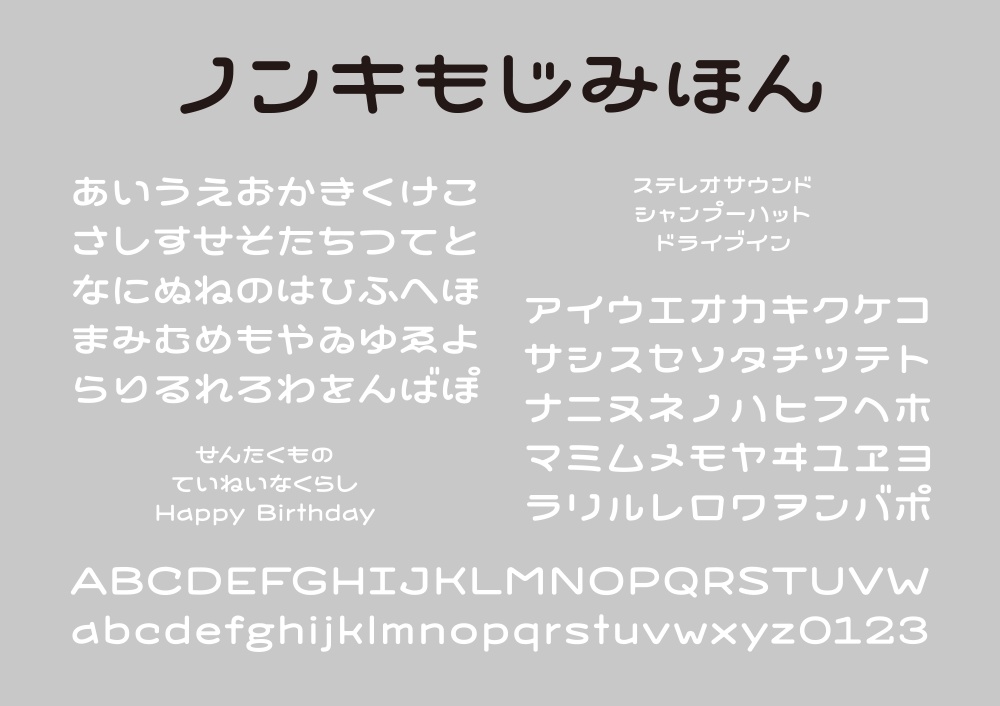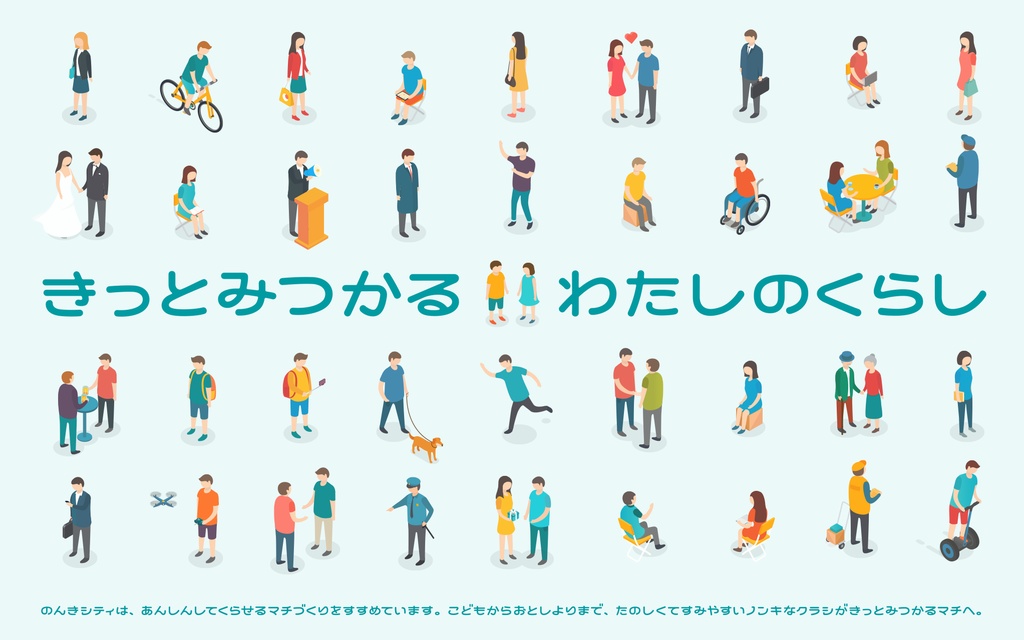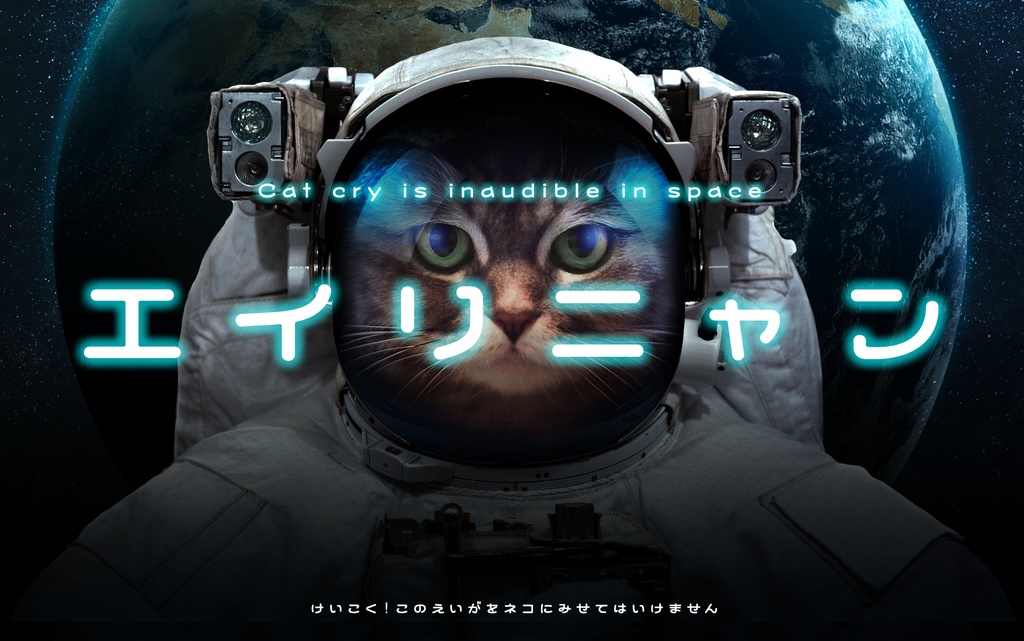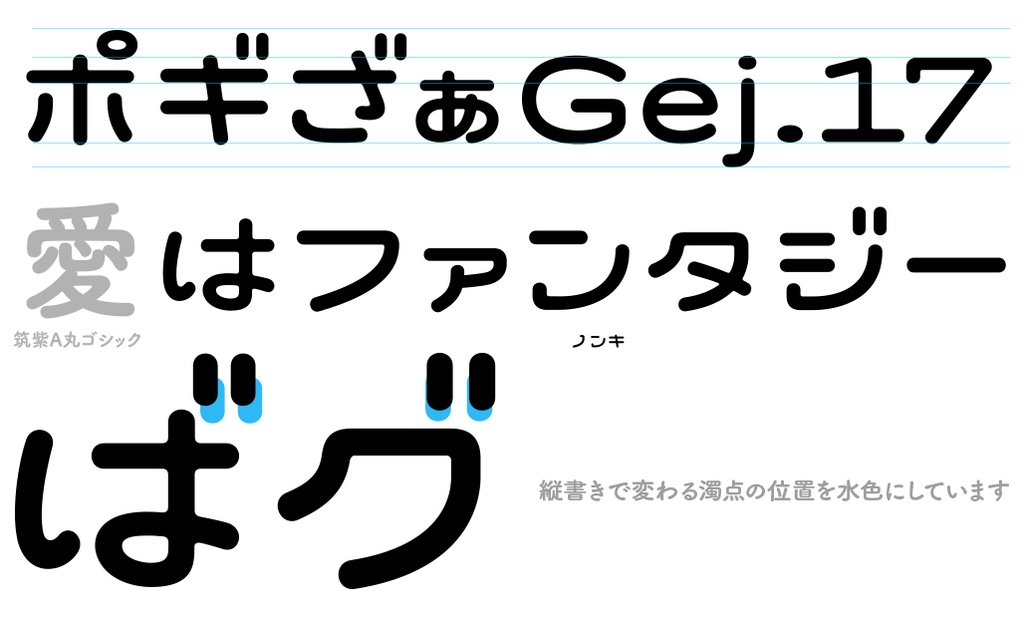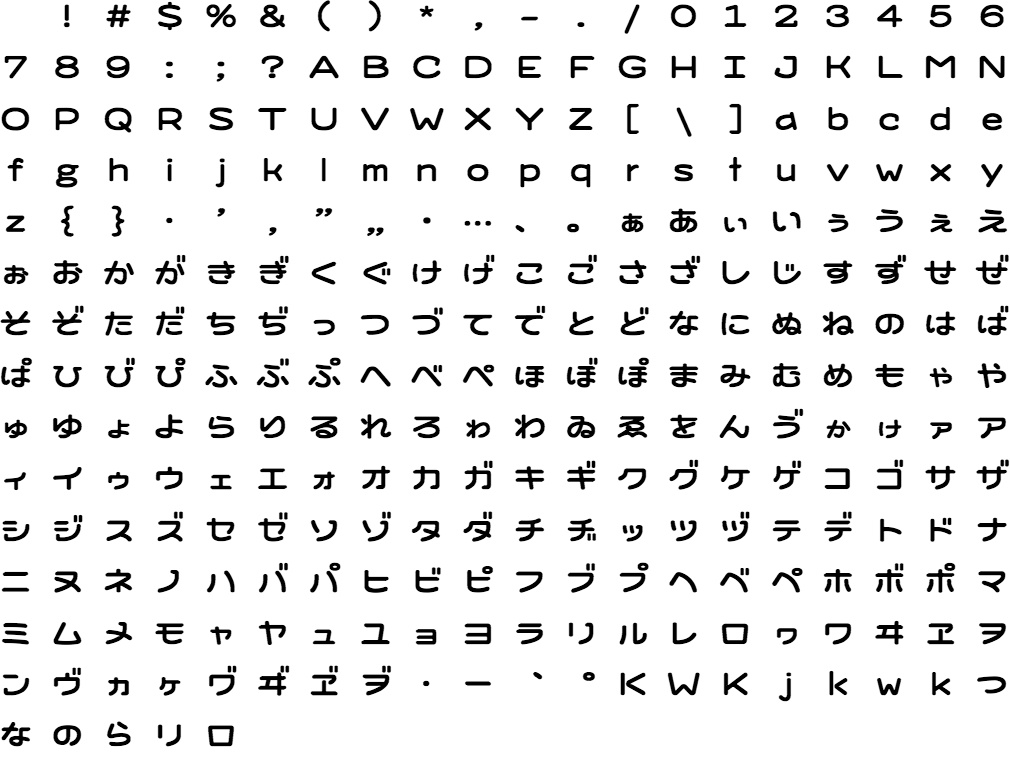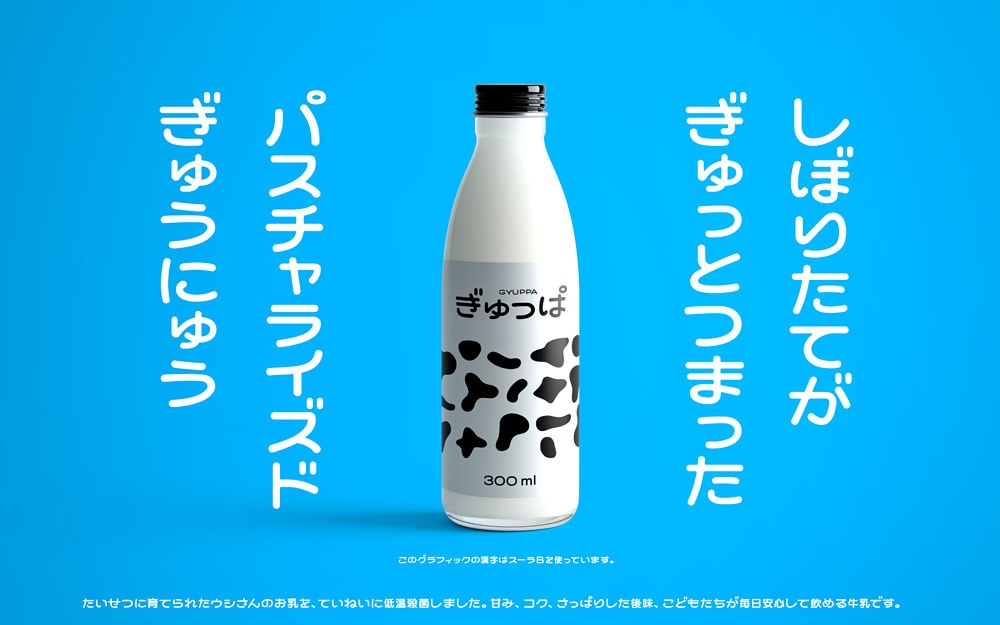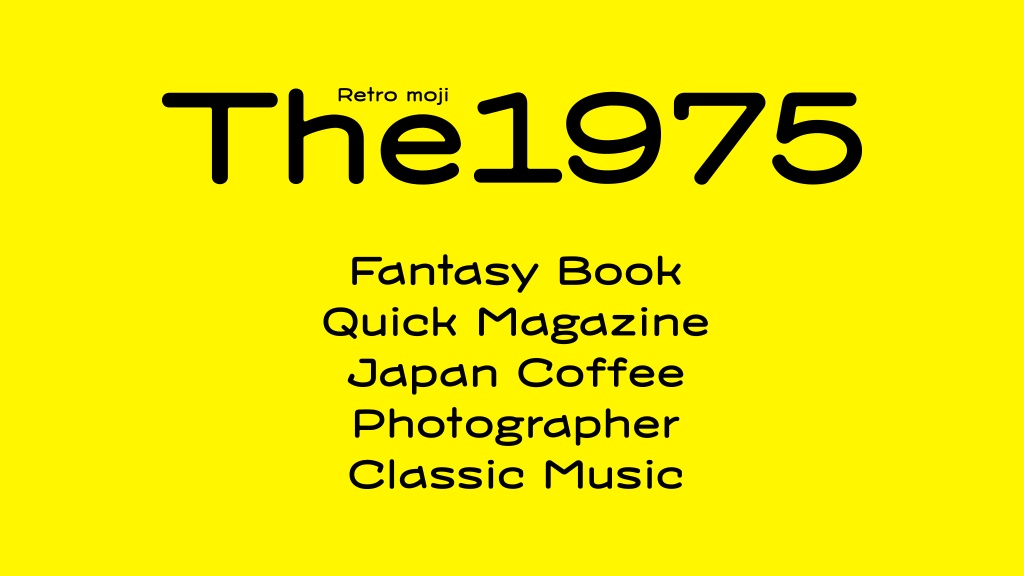
ノンキフォント
ノンキフォント のんきでかっこいい70年代風フォント 1970年代のテレビテロップ文字からインスピレーションを得て再生したフォント。少し横長で愛らしい、他に類を見ないフォントです。ロゴや見出し・ちょっとした説明文のフォントとして大活躍間違い無しのフォントです。 ■動作環境 Mac:システム/OS X対応(10.x)〜最新のOS X Windows:OS/日本語版Windows2000、XP、VISTA、Windows7〜11以降 フォント形式:OpenTypeフォント、TrueTypeフォント ※Adobeイラストレーター、フォトショップはもちろんのことWindows用ワード・エクセル等でもご使用になれます。 1商品(1ライセンス)につき1ユーザー1PCのみがご利用いただけます。複数人で使用する場合は人数分をご購入ください。 ■収録文字数について 収録文字数369文字(ひらがな.カタカナ.アルファベット) 合計1フォント収録 安心して使えるロイヤリティフリーの書体 あらゆる商用・デザイン用途(印刷物・ゲーム・アプリ・映像・動画・ロゴ・同人作品)に使用できる、商用申請の必要のないロイヤリティフリーの書体になります。文字の加工・変形も可能です。ご安心ください。 ■文字デザイン 揃えられた横線と、手描きのような曲線の対比が特徴です。そのおかげで、すごくレトロなのに未来的なデザインになっています。使い方次第でまったく印象の異なるデザインが作れると思います。また縦組みでは、濁点のデザイン・位置が異なるようにデザイン。アルファベットは日本語のようなデザインで、かわいさが際立っています。漢字は丸ゴシック体と組み合わせてお使いください。 ひらがな、カタカナ、アルファベットの大きさは揃えて、テロップなどで使いやすいようにしました。アルファベットは、タイプライターの文字のようなキュートなデザイン。動画やゲームの字幕や印刷物の説明文のフォントとして大活躍間違い無しのフォントです。 ■OpenType機能 詰め組み機能 ペアカーニング(仮名・プロポーショナル欧文) 字形切り替え機能(1つの文字で異なる字形を用意しています。異体字合計13種) ■グリフ 全369字(アルファベット、ひらがな、カタカナ、約物の一部)。漢字は収録されていないのでAdobe Illustrator、Adobe InDesignなどのアプリケーションで任意の漢字のフォントを組み合わせてご利用ください。